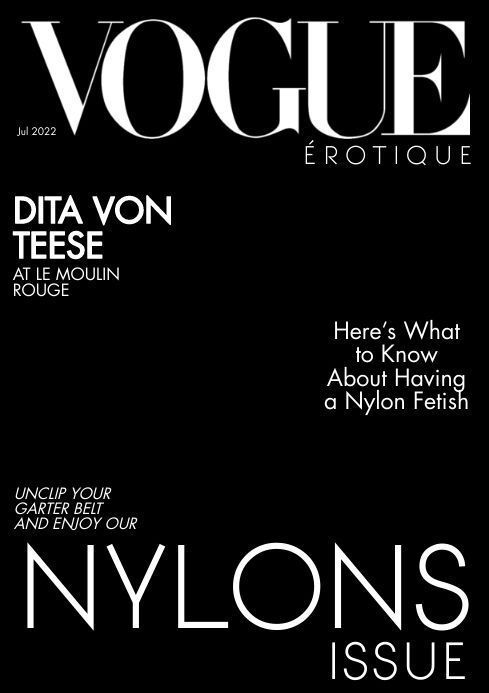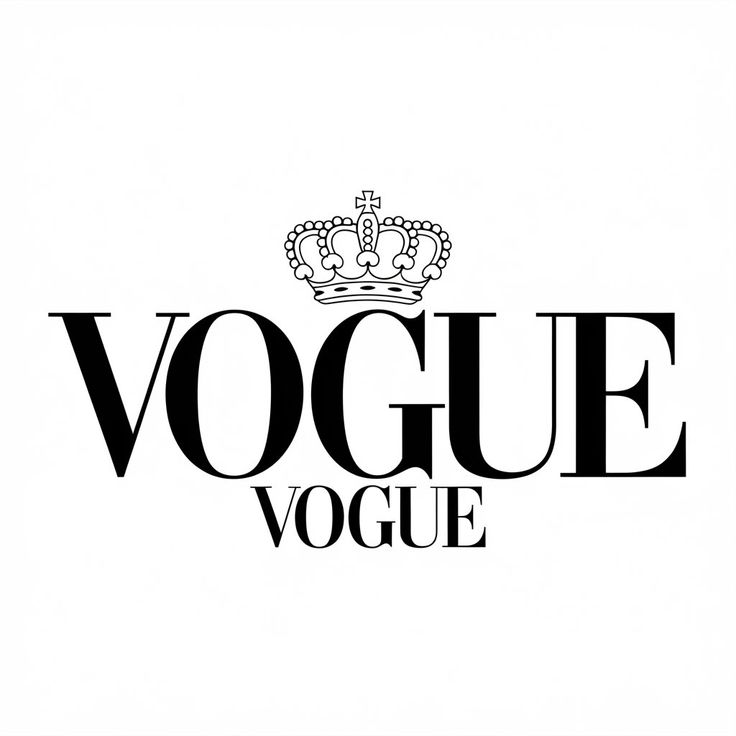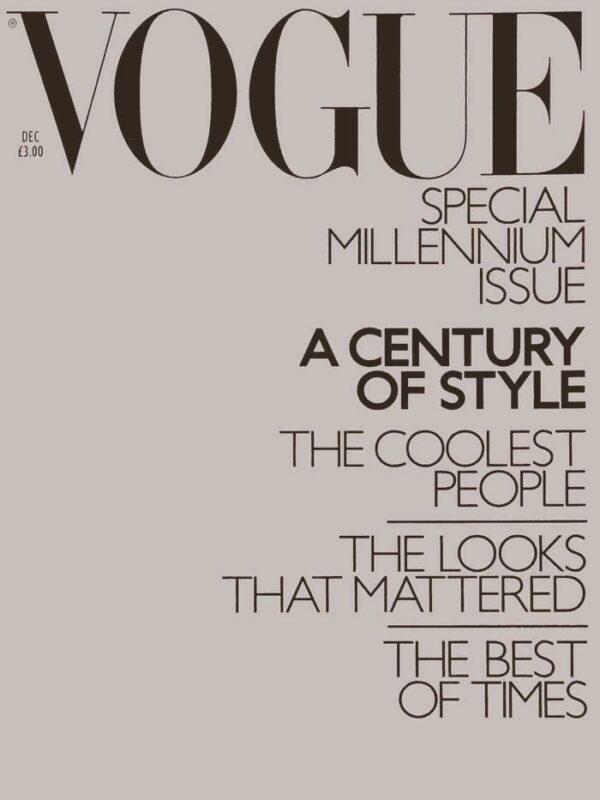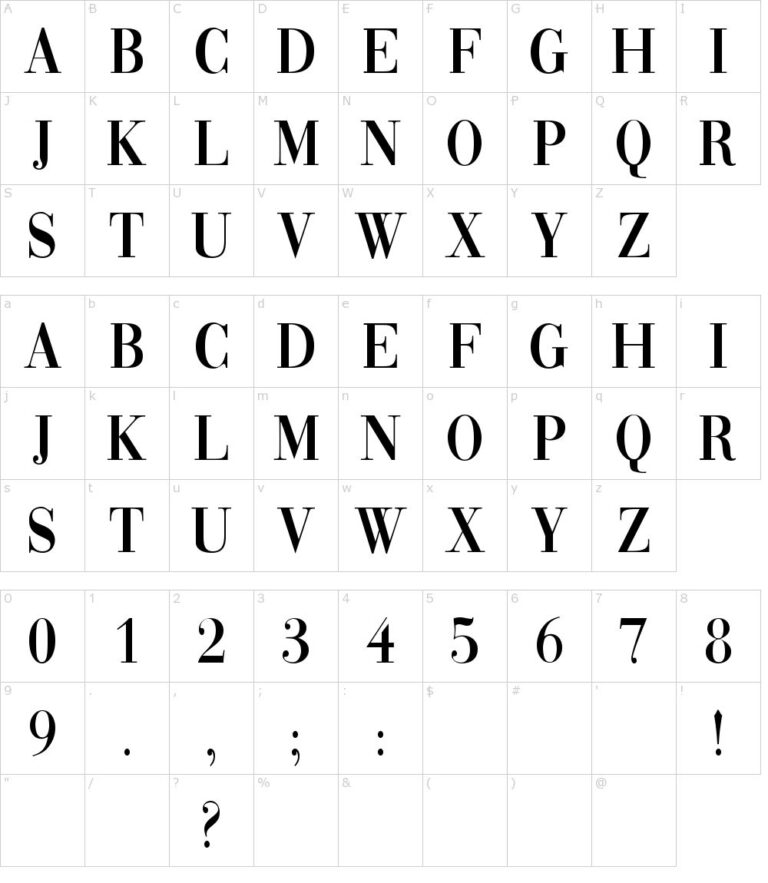
Vogue font là biểu tượng kinh điển của dòng Modern Serif gắn liền với tạp chí thời trang danh giá trên thế giới, nổi bật với sự tương phản sắc sảo giữa các cột chữ đậm đà và những đường chân chữ mảnh mai như sợi tơ. Với phong thái quý phái, xa hoa và đậm tính nghệ thuật đương đại, kiểu chữ này giúp các kiến trúc sư, nhà thiết kế nâng tầm thẩm mỹ cho các bản vẽ phối cảnh biệt thự nghỉ dưỡng, sảnh đón tiếp khách sạn boutique hay bìa hồ sơ năng lực dự án.
Tỷ lệ quý phái và sự tương phản cao của Vogue font trong thiết kế
Điểm cuốn hút của Vogue font nằm ở cấu trúc hình học chuẩn xác kết hợp cùng các đường chân chữ nằm ngang sắc bén, loại bỏ hoàn toàn các góc bo chuyển tiếp để tạo nên hiệu ứng thị giác dứt khoát và thời thượng. Tỷ lệ các ký tự được căn chỉnh theo chuẩn mực của thời trang cao cấp, mang lại cảm giác kiêu kỳ và sang trọng cho từng dòng tiêu đề.
Sự ổn định về mặt thị giác của dòng font này tạo nên phong thái lịch lãm, tin cậy và khẳng định đẳng cấp riêng biệt của chủ đầu tư. Khi xuất hiện trên các bề mặt vật liệu kiến trúc sang trọng như đá cẩm thạch trắng vân mây, inox mạ vàng xước mờ, kính cường lực phản quang trong các công trình nhà lắp ghép cao cấp, Vogue tạo nên điểm nhấn thị giác cuốn hút.
| Phân loại phong cách | Modern Serif / Didone / Luxury Fashion |
| Mục đích phù hợp | Biển tên villa cao cấp, bìa hồ sơ năng lực, logo |
Tư vấn từ chuyên viên: Vogue font sở hữu các nét thanh cực kỳ mỏng và độ tương phản lớn. Để bản thiết kế đạt hiệu quả thẩm mỹ tốt, bạn nên sử dụng phông chữ này cho các tiêu đề chính, tên dự án hoặc câu slogan ngắn ở kích thước lớn.
03 Ứng dụng phông chữ Vogue vào công trình thực tế
Nhờ vẻ ngoài quý phái và tính thẩm mỹ cao cấp, bộ phông chữ này mang lại giá trị thực tế lớn trong khâu tạo điểm nhấn cho các công trình hiện đại:
- Biển hiệu mặt tiền cho Showroom Thời trang và Villa Nghỉ dưỡng: Những nét chữ thanh lịch của Vogue rất ăn ý khi gia công chữ nổi bằng inox vàng gương hoặc khắc chìm trên đá hoa cương, giúp căn nhà lắp ghép toát lên vẻ đài các và thu hút sự chú ý của du khách.
- Bìa hồ sơ năng lực dự án kiến trúc: Sử dụng Vogue font cho tên dự án và tiêu đề các chương mục giúp hồ sơ trông như một ấn phẩm tạp chí danh giá, thể hiện gu thẩm mỹ tinh tế và năng lực của đơn vị kiến tạo.
- Hệ thống biển tên phòng và bảng chỉ dẫn nội khu: Phông chữ này khi in trên kính mờ hoặc kim loại phủ sơn tĩnh điện sẽ giúp không gian sảnh đón tiếp và hành lang toát lên chất nghệ thuật thanh lịch.
03 Lưu ý bố cục Vogue free font duy trì trọn vẹn nét thanh tao
Để khai thác hiệu quả vẻ đẹp của dòng font thời trang quý tộc này mà không làm ảnh hưởng đến khả năng đọc của bản vẽ, người thiết kế nên lưu tâm một số kinh nghiệm sau:
- Tránh sử dụng ở kích thước quá nhỏ: Do có các nét thanh mảnh như sợi chỉ, Vogue hiển thị đẹp ở kích thước chữ từ 16pt trở lên trong in ấn. Ở kích thước quá nhỏ, nét thanh có thể bị mờ nhòe do độ phân giải máy in hoặc thớ giấy.
- Nới rộng khoảng cách ký tự: Đối với các tiêu đề viết hoa toàn bộ, việc kéo giãn nhẹ khoảng cách giữa các chữ cái sẽ làm tăng tính trang nghiêm, giúp bố cục thông thoáng và mang đậm phong thái kiến trúc đương đại.
- Bố trí nền màu đơn sắc tương phản: Vogue phát huy hiệu quả thị giác cao khi đặt trên các nền màu đơn sắc có chiều sâu như đen tuyền, trắng ngọc trai, xám than hoặc xanh rêu sẫm, giúp các đường nét sắc sảo của bộ chữ được tôn vinh rõ ràng.
FAQs – Thắc mắc thường gặp khi sử dụng phông chữ Vogue
1. Font Vogue có dùng được trên ứng dụng Canva không?